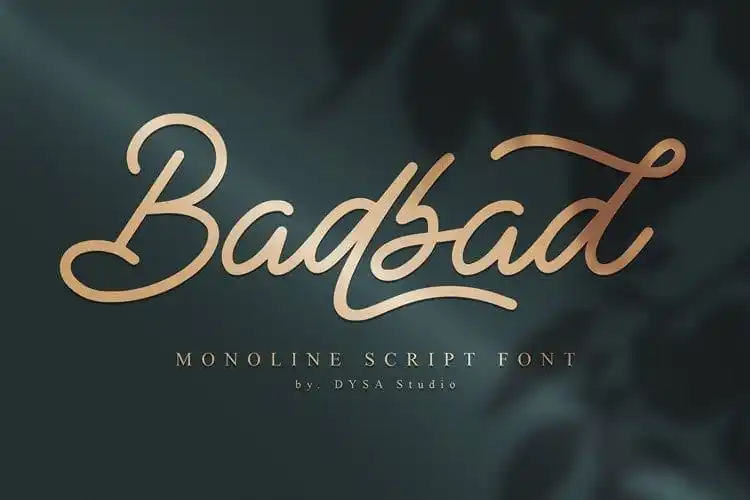
Badbad Script Font – Download Grátis
A Badbad Script Font é uma elegante fonte de script monolínea criada pelo DYSA Studio, que transmite sentimentos autênticos e descontraídos. Esta fonte vem para reforçar seu próximo projeto de marca, sendo perfeita tanto para “logotipo” quanto para trabalhos mais elaborados em estilo script. Com uma sensação casual mas sempre elegante, a Badbad Script Font é ideal para quem busca uma fonte versátil e moderna que complementará sua identidade visual de maneira impecável. Seja você um designer profissional ou um iniciante que quer dar um toque único em seu próximo projeto de arte digital, essa fonte não pode faltar no seu arsenal de recursos.